Как использовать курсивную гарнитуру в логотипе и заголовке
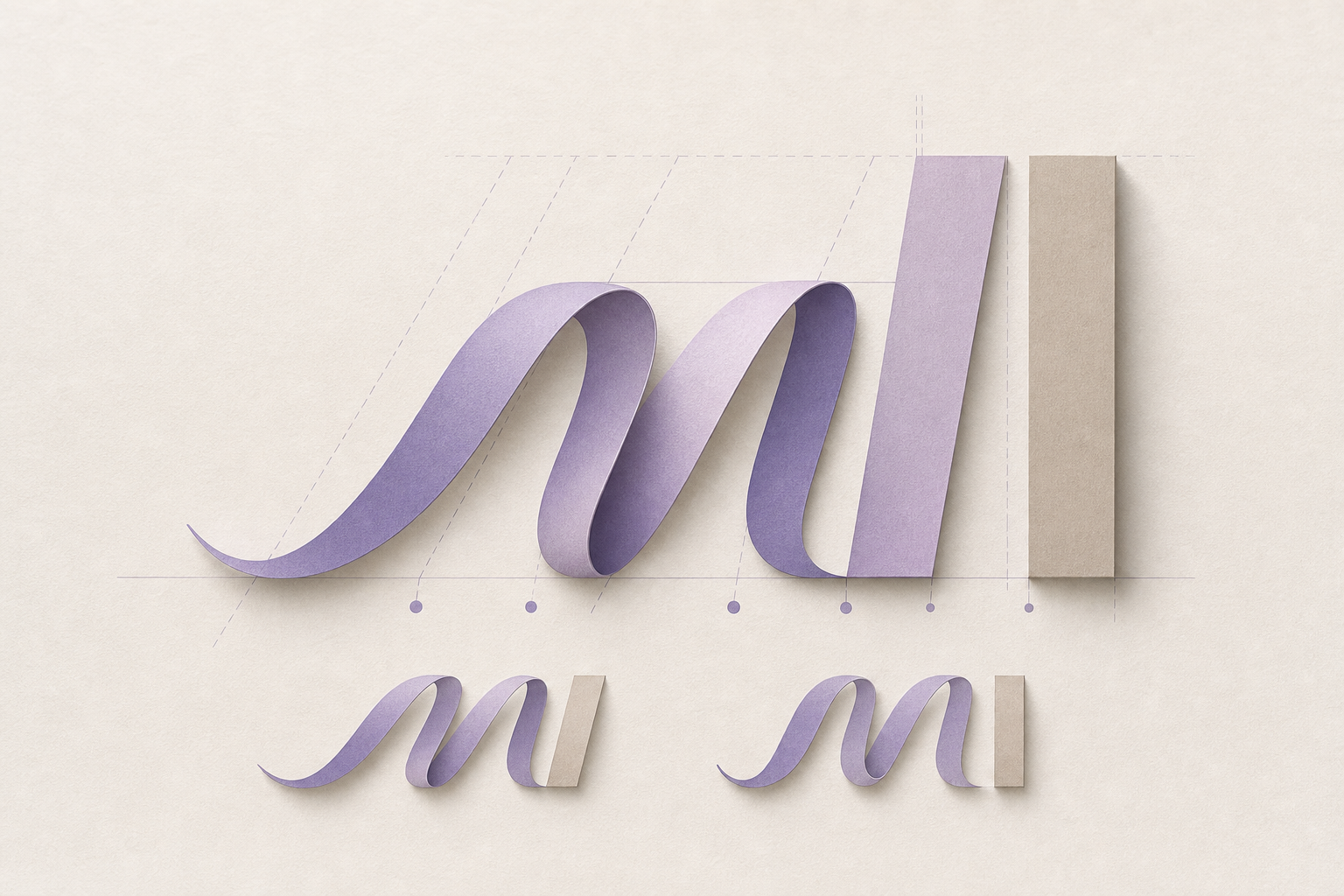
Курсивная гарнитура уместна в логотипе и заголовке, если она поддерживает характер бренда, а не просто украшает текст. Наклонные буквы передают движение, эмоциональность, элегантность или ощущение ручной работы. Чтобы композиция оставалась профессиональной, важно проверить читаемость, длину названия, контраст с прямым шрифтом, интервалы и поведение надписи в разных размерах.
Что передаёт курсивная гарнитура в айдентике
Курсивное начертание отличается от прямого не только наклоном. В хорошо спроектированной курсивной версии могут меняться формы отдельных букв, соединения, ширина знаков и ритм строки. Поэтому такой шрифт воспринимается как более живой и выразительный. Он подходит брендам, которым нужно подчеркнуть скорость, мягкость, премиальность, творческий подход или персональный характер коммуникации.
Однако эмоциональность не равна универсальности. Курсивная надпись сложнее читается в маленьком размере, на пёстром фоне и при слабом контрасте. Особенно это заметно в длинных названиях, словах с большим количеством узких букв и текстах, набранных декоративным скриптом. Поэтому курсив лучше использовать как управляемый акцент, а не автоматически применять ко всему фирменному тексту.
Когда наклонный шрифт подходит логотипу
Выбор курсивной гарнитуры начинается с позиционирования. Если бренд обещает динамику, индивидуальный сервис, ручную работу или визуальную изысканность, наклонное начертание может усилить это сообщение. Для технологичной компании курсив иногда подчёркивает скорость и движение, для студии красоты — пластичность, для кафе или мастерской — человеческий и неформальный тон.
- Используйте курсив, когда бренду нужны выразительность, энергия или ощущение личного почерка.
- Проверяйте, не противоречит ли декоративность обещанию бренда и ожиданиям аудитории.
- Откажитесь от слишком сложной формы, если логотип должен работать на упаковке, вывеске и в интерфейсе.
- Сохраняйте прямую версию названия как резервный вариант для маленьких и технически ограниченных носителей.
Как выбрать курсивный шрифт для логотипа
Оцените характер букв и ритм слова
Сначала наберите в понравившемся шрифте настоящее название бренда, а не случайный пример. Одна и та же гарнитура может выглядеть убедительно в коротком слове и неразборчиво в длинном. Посмотрите на форму заглавной буквы, соединения между знаками, высоту строчных, выносные элементы и плотность строки. В логотипе важен не внешний вид алфавита вообще, а конкретный рисунок названия.
Различайте настоящий курсив и механический наклон
Настоящий курсив обычно проектируется как отдельное начертание, поэтому его буквы имеют собственную пластику. Механический наклон прямого шрифта лишь поворачивает исходные знаки и часто создаёт неестественный ритм. Для фирменного знака предпочтительнее полноценная italic-версия, если она существует. Если используется декоративная гарнитура, обязательно проверяйте кириллицу: качество латинских букв не гарантирует хорошую форму русских знаков.
Проверьте техническую устойчивость
Логотип должен сохранять узнаваемость в чёрно-белом варианте, на экране смартфона, в favicon, на визитке и в крупной наружной печати. Тонкие штрихи могут исчезать, а плотные соединения — сливаться. Уменьшите надпись до предполагаемого минимального размера и проверьте её на расстоянии. Если слово превращается в декоративную полосу, упростите композицию или подготовьте компактную версию.
Как строить логотип с курсивной надписью
В текстовом логотипе курсивная гарнитура может использоваться для всего названия, одного слова или короткого дескриптора. Часто наиболее устойчиво работает контраст: название набирают выразительным курсивом, а поясняющую строку — спокойным прямым гротеском. Такое решение разделяет уровни информации и не заставляет зрителя расшифровывать всю композицию одним усилием.
Настройте кернинг вручную
Автоматические интервалы редко дают идеальный результат в коротком логотипе. Наклон меняет визуальное положение букв: одни знаки словно выступают вперёд, другие оставляют заметные пустоты. Отрегулируйте пары с диагональными, округлыми и узкими элементами, затем оцените не расстояние между контурами, а равномерность белого пространства. После этого проверьте надпись в кривых или в другом финальном формате.
Соблюдайте оптическое выравнивание
Курсивная строка часто визуально смещается вперёд из-за наклона и выступающих штрихов. Геометрически выровнять её по краям недостаточно: логотип может казаться заваленным или слишком близким к символу. Сравните текст и знак на расстоянии, уменьшите масштаб и при необходимости сдвиньте элементы вручную. В логотипе оптическое равновесие важнее математической симметрии.
Как использовать курсив в заголовках
В заголовке курсивная гарнитура должна помогать быстро понять иерархию, а не конкурировать с содержанием. Для длинных заголовков лучше выбирать умеренно наклонный шрифт с открытыми формами и устойчивой кириллицей. Декоративный скрипт оставляйте для коротких фраз, рубрик, обложек и акцентных слов. Основной текст рядом набирайте более нейтральной гарнитурой.
Курсивная гарнитура эффективно работает в логотипе и заголовке, когда её наклон связан с характером бренда, а выразительность не жертвует читаемостью. Начинайте с реального названия, проверяйте кириллицу, настраивайте интервалы вручную и заранее готовьте версии для разных размеров и носителей. Если нужен индивидуальный визуальный голос, создайте собственный шрифт на fontgenerator.ru и используйте его как основу узнаваемой айдентики.